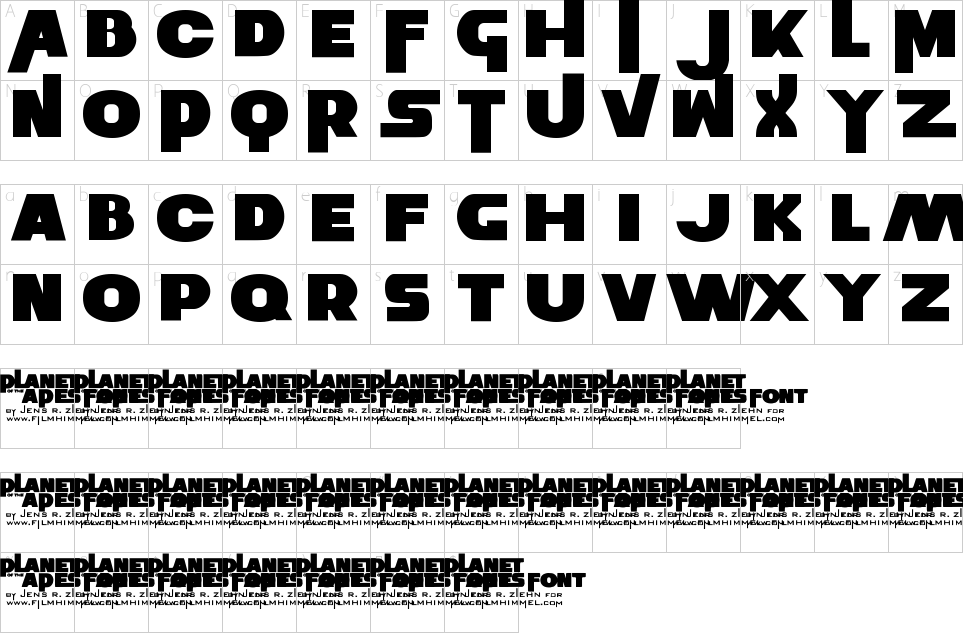
Descubra a fonte Planet Of The Apes, inspirada no filme icônico, agora disponível em versões para Windows e Mac. Esta fonte foi projetada por Jens R. Ziehn do Studio Film Himmel. É perfeita para aqueles que desejam incorporar um toque distinto e único em seus projetos digitais. Desde seu lançamento, a fonte Planet Of The Apes foi baixada mais de 92.832 vezes, demonstrando seu valor e popularidade entre criadores de conteúdo. Seja para aplicativos, design gráfico ou publicidade, esta fonte oferece uma opção versátil e emocionante para adicionar personalidade e originalidade a seus projetos. Não perca esta oportunidade de ganhar mais destaque com Planet Of The Apes Font.